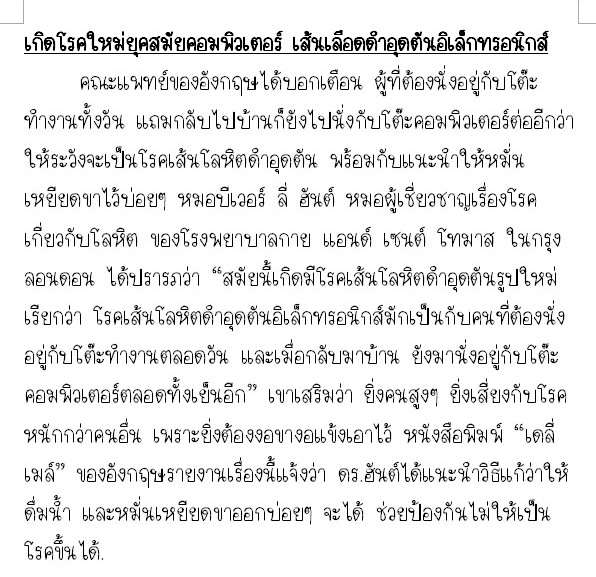
ฟอนต์เสร็จแล้วมีปัญหาอย่างนึงอะคะ
ทำไอคอน พรีวิว ฟอนต์เสร็จหมดแล้วแต่ว่าเวลาพิมพ์ในคอมแล้วตัวหนังสือหนาบางไม่เท่ากันอะค่ะ พอเวลาปริ้นออกมาแล้วไม่ป็นอะแก้ตามที่เค้าบอกมาก็ไม่หายอะคะจะทำยังไงดีคะ เอาพรีวิว ไอคอนแล้วก็ปัญหามาให้ดูด้วยคะ
เคยแก้ตามที่บอกมาแล้วอะค่ะ แต่ว่าไม่หายจะทำยังไงอะค่ะ ปล.ขอโทษอีกทีละกันนึกว่านี่ตั้งสื่อความหมายแล้วอะค่ะ ต่อไปจะเอาให้ชัดเจนชัดๆๆเลยขอโทษค่ะ ช่วยหาวิธีแก้ให้หน่อยซิคะหรือว่าไม่ต้องแก้เพราะว่าเวลาปริ้นออกมาก็ไม่เป็นอะค่ะ
"เวลาพิมพ์ในคอมแล้วตัวหนังสือหนาบางไม่เท่ากันอะค่ะ"
น่าจะถามอย่างนี้ครับ
ส่วนเรื่องความหนาบางของฟอนต์ใช้วิธีฮินติงได้ไหมครับ
แก้แล้วค่ะมันหายบางตัวอะ บางตัวก็ไม่หาย พอเวลาพิมพ์แล้วหนาบางไม่เท่ากันแต่พอปรับขนาดใหญ่อีกนิดนึงก็เท่ากันนะคะ เกี่ยวกับ hinting รึเปล่าค่ะเช่นพิมพ์ตัวขนาด24ตัวป.จะหนาไม่เท่ากันแต่พอปรับขนาดเป็น25ตัวป.จะหนาเท่ากันอย่างงี้อะคะ
แล้วจะต้องแก้ไขยังไงอะค่ะ เพราะบางตัวมันก็แก้ได้บางตัวมันก็แก้ไม่ได้อะ
ตรงไหนที่เส้นหนา
ปรับให้ความกว้างของเส้นคู่ตรงนั้นมันน้อยลงไปอีกครับ
วิธีการคือกดคลิกขวาที่ตรงเส้นเขียว แล้วคลิกที่ Properties ตรงช่อง Width
กำหนดให้มันน้อยลงกว่าเดิมไปอีก จนดูในคอมแล้วเส้นไม่แตก